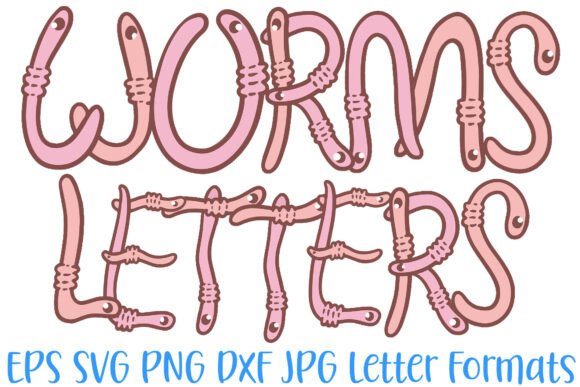
Worm Letters Font Comic Wiggly Letters
Пошук відповідних елементів дизайну може бути складним, але Worm Letters Font Comic Wiggly Letters пропонує виняткову колекцію, яка миттєво покращить вашу роботу.
Незалежно від того, чи створюєте ви продукти POD (друк на вимогу), весільні запрошення або графіку для соціальних мереж, Worm Letters Font Comic Wiggly Letters стане ідеальним вибором.